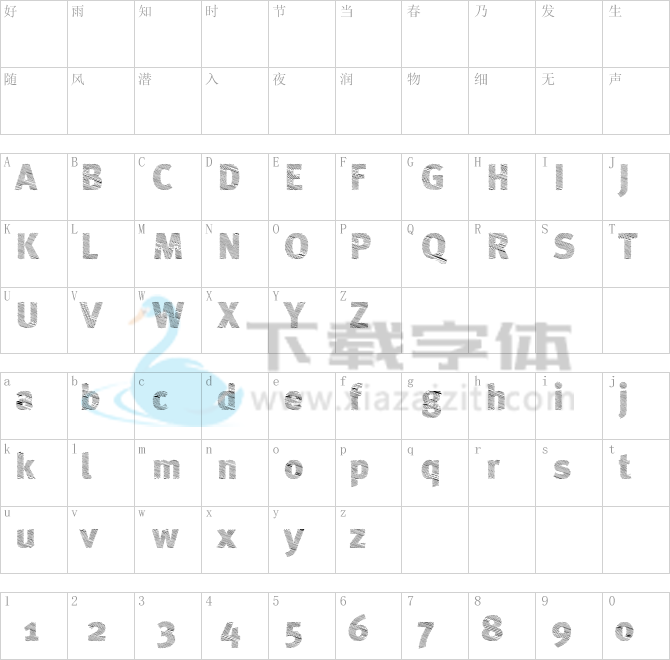
A Bebedera.ttf字体下载,这款字体结构工整、笔画清晰,兼顾美观与易读性,适用于标题、正文、海报、包装、LOGO 等多种场景。字形优雅稳定,风格百搭耐看,适配日常排版与创意设计,让文字呈现更舒适、更具质感。A Bebedera.ttf字体下载一笔一画,皆是细节,以均衡的比例、流畅的线条打造舒适视觉体验,字形端正大气,风格简约现代。无论是商业设计、品牌宣传还是日常排版,都能轻松驾驭,让文字更有格调与力量。A Bebedera.ttf字体下载字体下载。